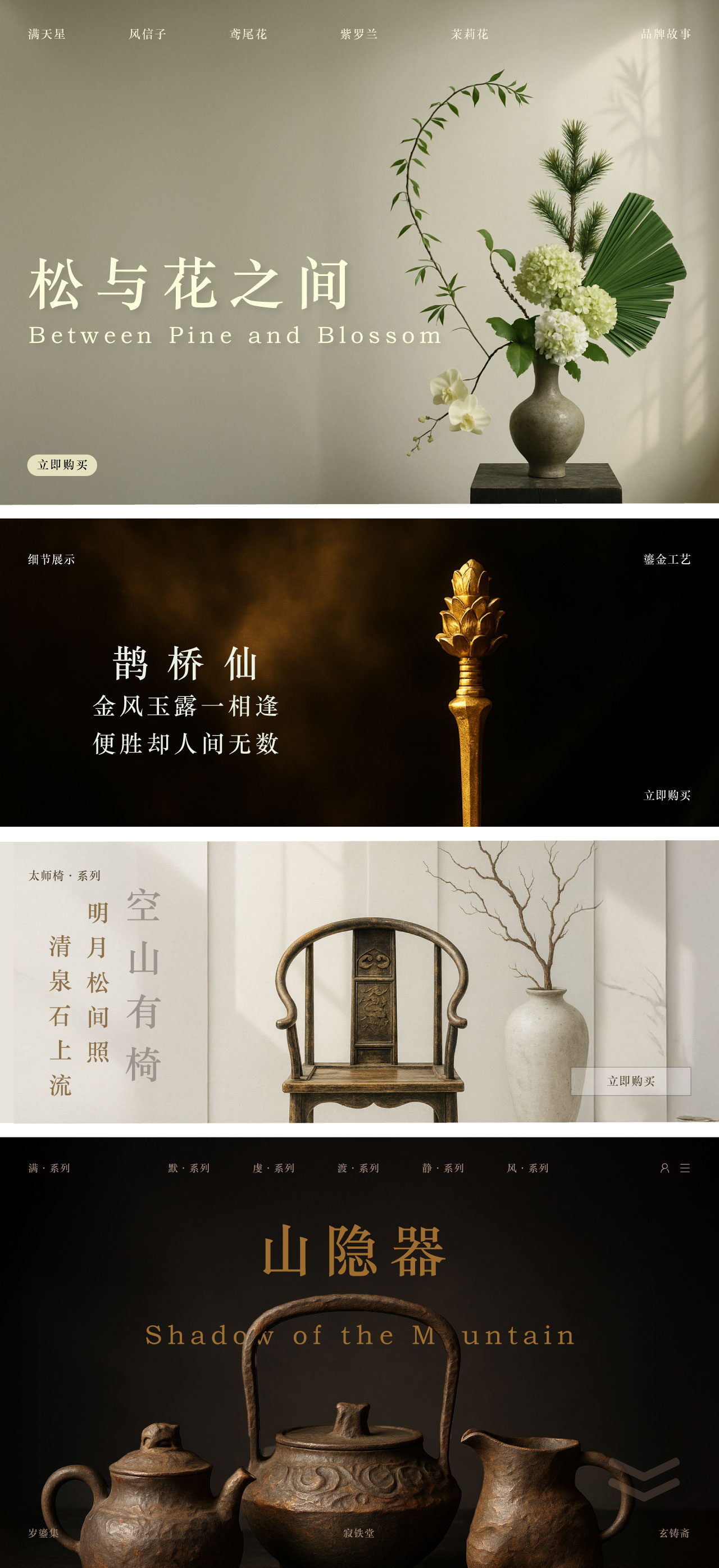
华文中宋 / STZhongsong / Bold
华文中宋
华文中宋 / STZhongsong
设计师:
常州华文
字体介绍:
华文宋体,雅致大方,字形具有一种方正雅观的特点,结构条理清晰;字符覆盖面广,覆盖了绝大部分汉字,包括一些生僻字;华文宋体的小字体清晰,可以清晰到12号字,而不失字体特点。
适用于商标设计、广告设计、报纸与图书等行业中,效果较好。